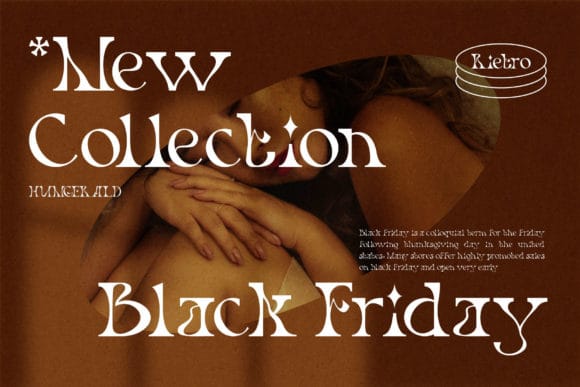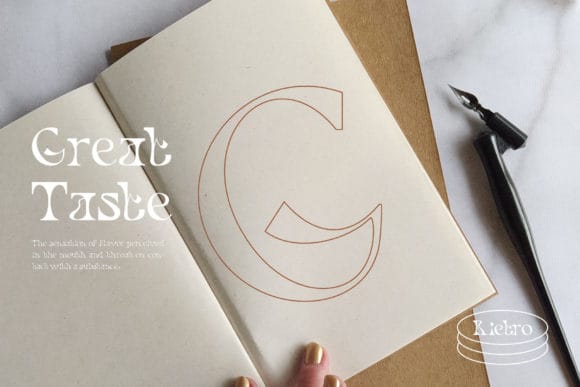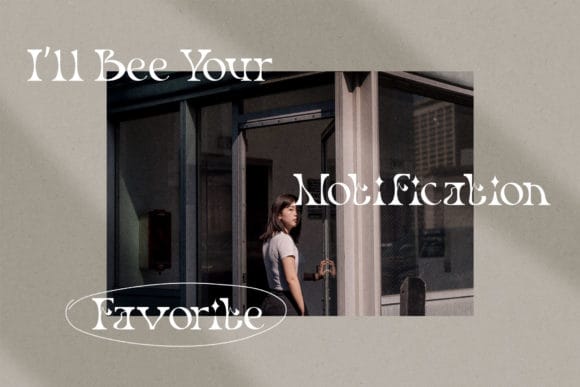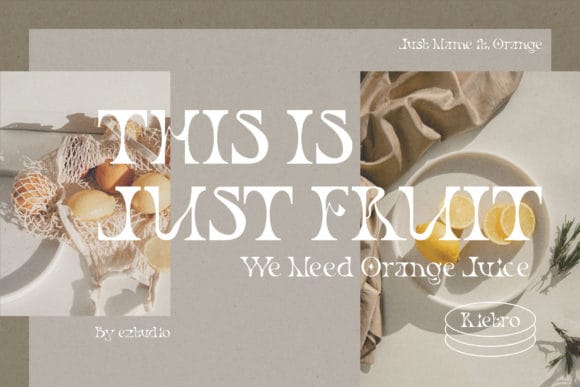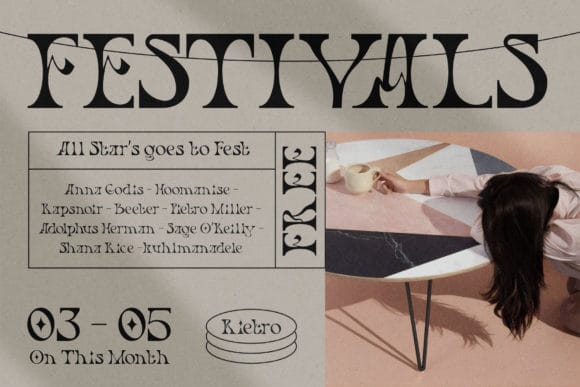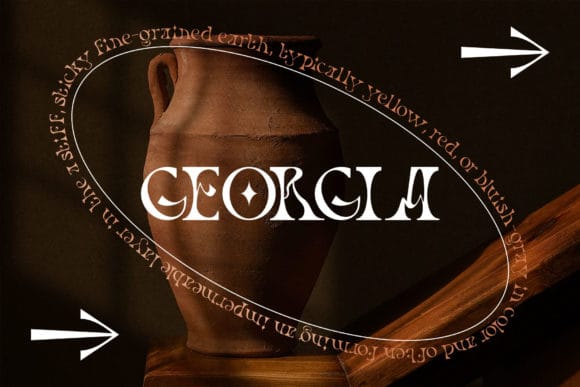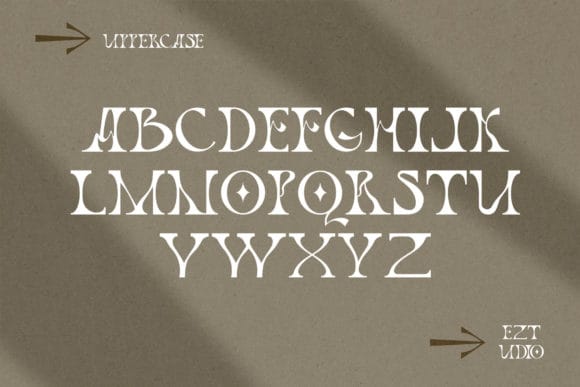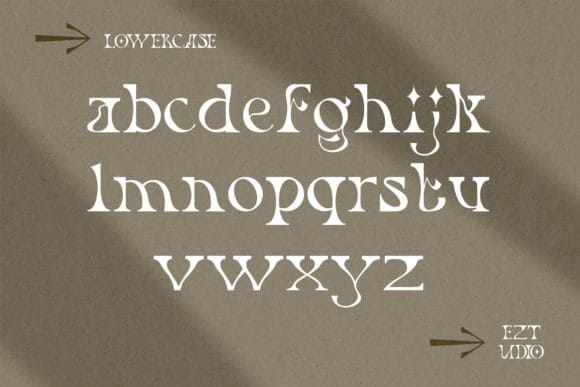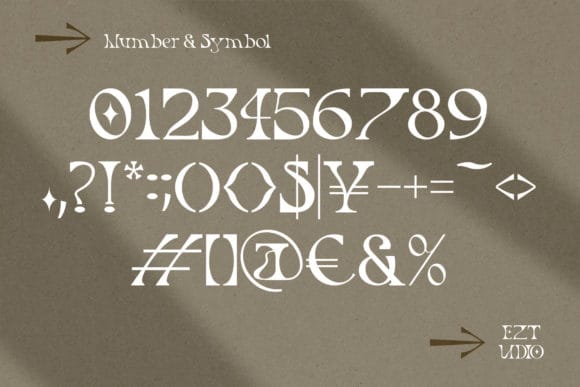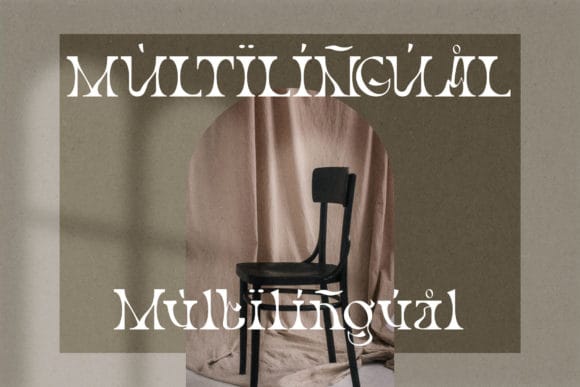
Rietro là một font chữ serif sang trọng và độc đáo với thiết kế lạ và ấn tượng. Nó có vẻ ngoài sang trọng, thanh lịch và hiện đại, có thể được sử dụng cho logo, thương hiệu, lời mời, văn phòng phẩm, thiết kế đám cưới, bài đăng trên mạng xã hội và hơn thế nữa!Font Rietro được thiết kế mang phong cách gothic với các đường nét khá đặc biệt tạo ra kiểu font chữ mới lạ và độc đáo. Mỗi đường nét đặc biệt của từng chữ cái khác nhau mang đến một điểm nhấn nhất định cho font.